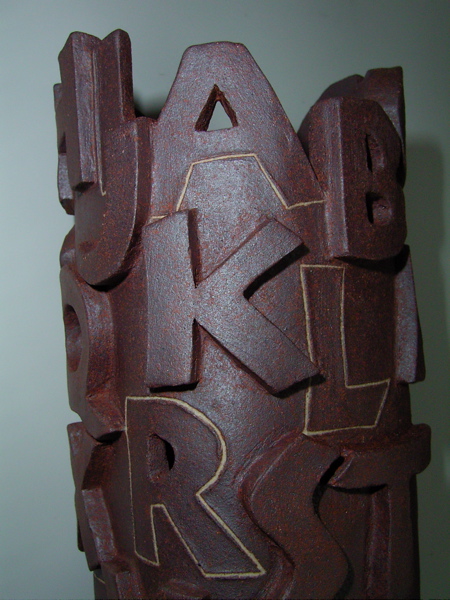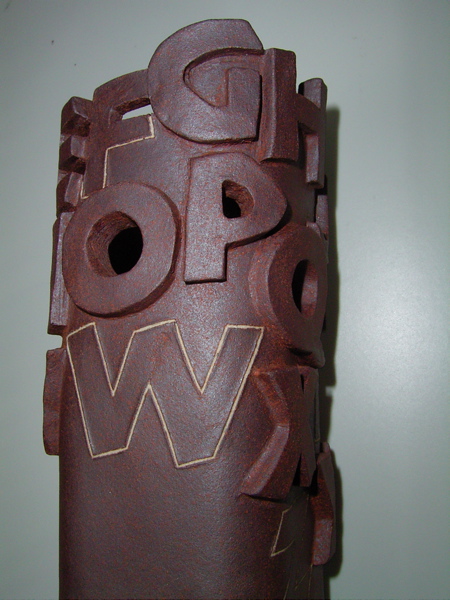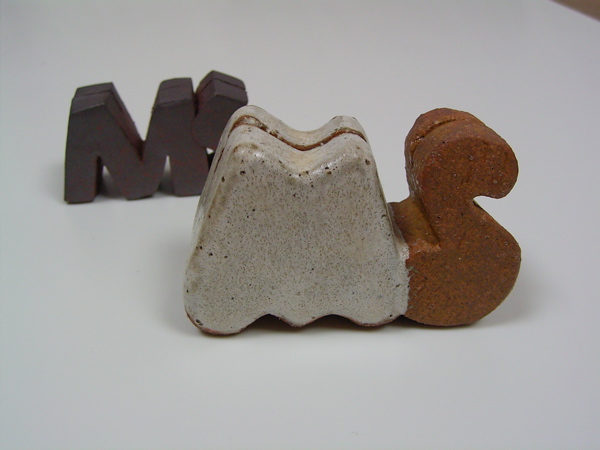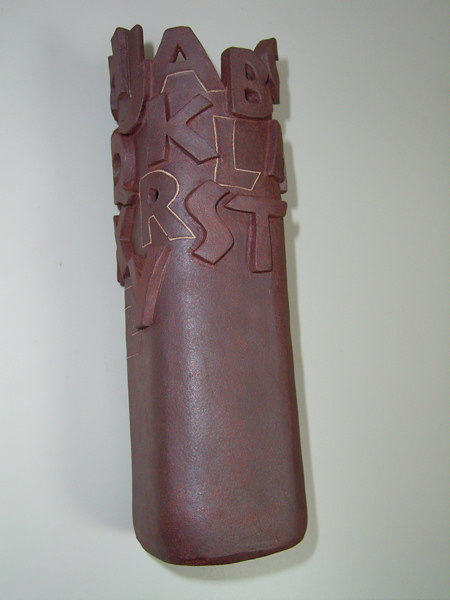
小松さんの陶器
ジャーン、小松千代子さんにお願いしていた陶器が届きました!
以前作品展に出展していたものを、お願いして作って頂いたのです。ノイランドの形がカワイイッ!作品展に出展していた方が色が赤かったそうですが、こちらもいい感じに赤茶けていて、まるでさびた鉄の様。
文字が飛び出ている所、本体そのものの厚みの部分、そして文字が書いてあったり穴が抜けていたり。一つでさまざまな顔を持っているから見ていて飽きないのです。
見る角度によっても文字が違うので、いろいろ楽しめますね。
特に穴の空いている文字が可愛い。RとかOとか。
ふふ、実は今回はオマケ付きでした。遠くに見えるのが今回おまけのカード立て。ラッキー!
そして手前にあるモコモコしたのも以前頂いた、こちらもカード立て。どちらも気に入ってます。
小松さんはカリグラファーでもありますが、最近は陶芸家としても活躍されています。文字は何とでも一緒になれますが、こうして陶芸としての発展も楽しみですね。まだまださらに進化していきそうです。本当に奥が深そう。これからも小松さんの作品に目が離せません。